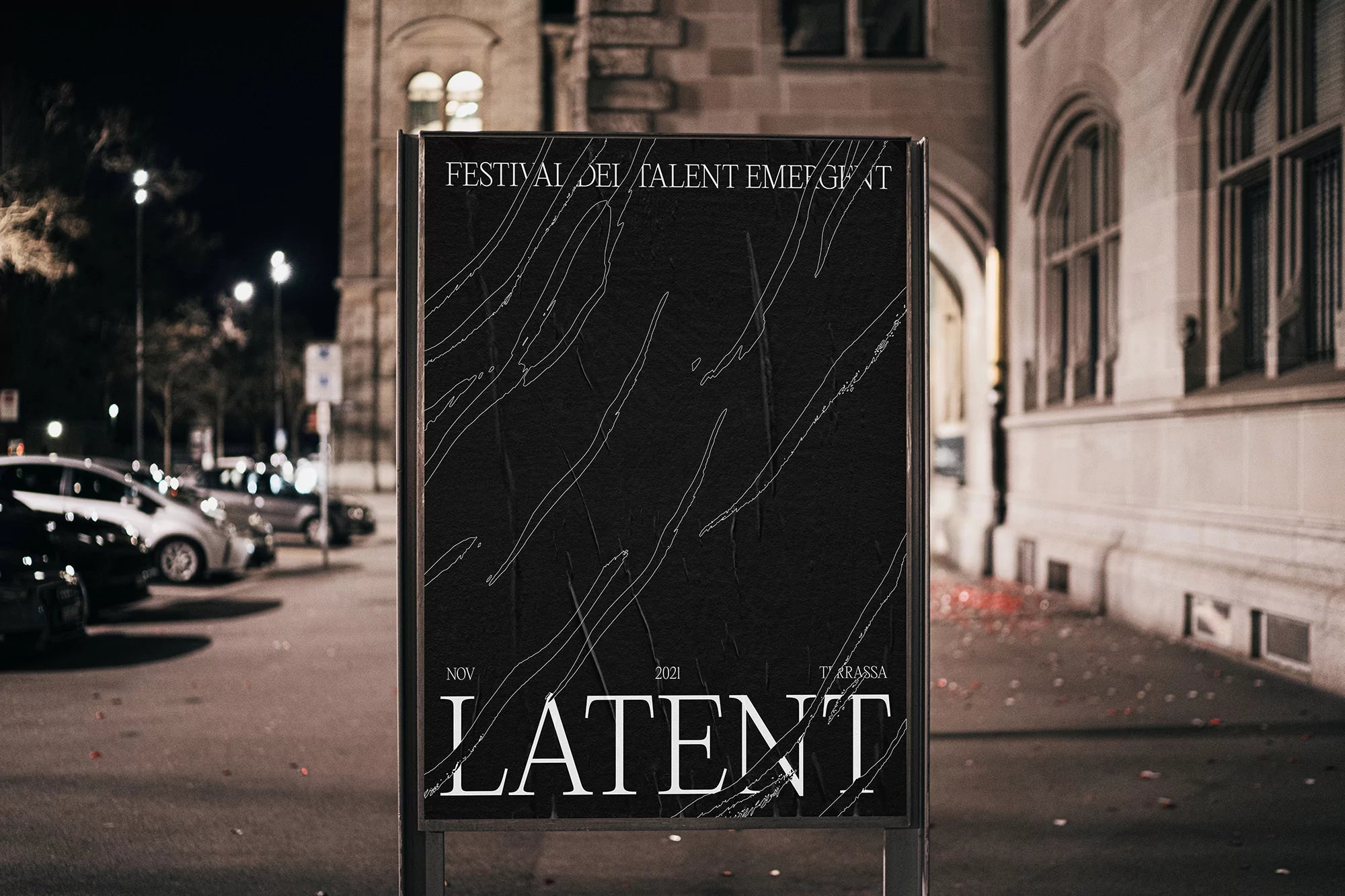
Le studio créatif basé à Barcelone Bakoom s'est associé au festival de design et de créativité de Catalogne LATENT pour créer le système d'identité immersif de l'événement.
Conceptuellement guidé par la définition du dictionnaire du nom du festival, Bakoom a développé une identité poignante, stratifiée et graphiquement texturée pour incarner cette dernière.
« Latent signifie "existant mais pas encore développé ou manifesté ; caché ou dissimulé" », explique la graphiste Sandra Llopart. « Partant de ce concept, nous avons créé un système visuel où tout se déroule sur une seconde couche », ajoute-t-elle, « ce qui témoigne de son désir d'être présent et observé », créant ainsi un espace puissant où l'identité peut s'exprimer comme un système à part entière et, surtout, renforcer la créativité défendue lors du festival.
Principalement numérique dans ses applications, Bakoom a également créé des applications cinétiques vivantes à travers son identité, donnant lieu à une exploration fascinante et hypnotique de la forme, de la texture et du mouvement. Ce dynamisme contemporain contraste fortement avec l'application austère de la typographie, offrant à l'identité une base solide et pragmatique sur laquelle les animations peuvent s'épanouir. « Nous avons choisi Editorial New », explique Llopart à propos du choix de la police. « C'est une police fine et élégante qui donne de la personnalité », ajoute-t-elle, « et qui s'impose dans les titres. » L'utilisation délicate de la couleur par Bakoom harmonise ces deux forces, insufflant une forte impression de modernité numérique à toute la marque. « Nous avons créé un jeu de contrastes avec le noir, le blanc et le violet », conclut Llopart, « pour représenter l'élégance, la force et la beauté, et obtenir un look moderne. »